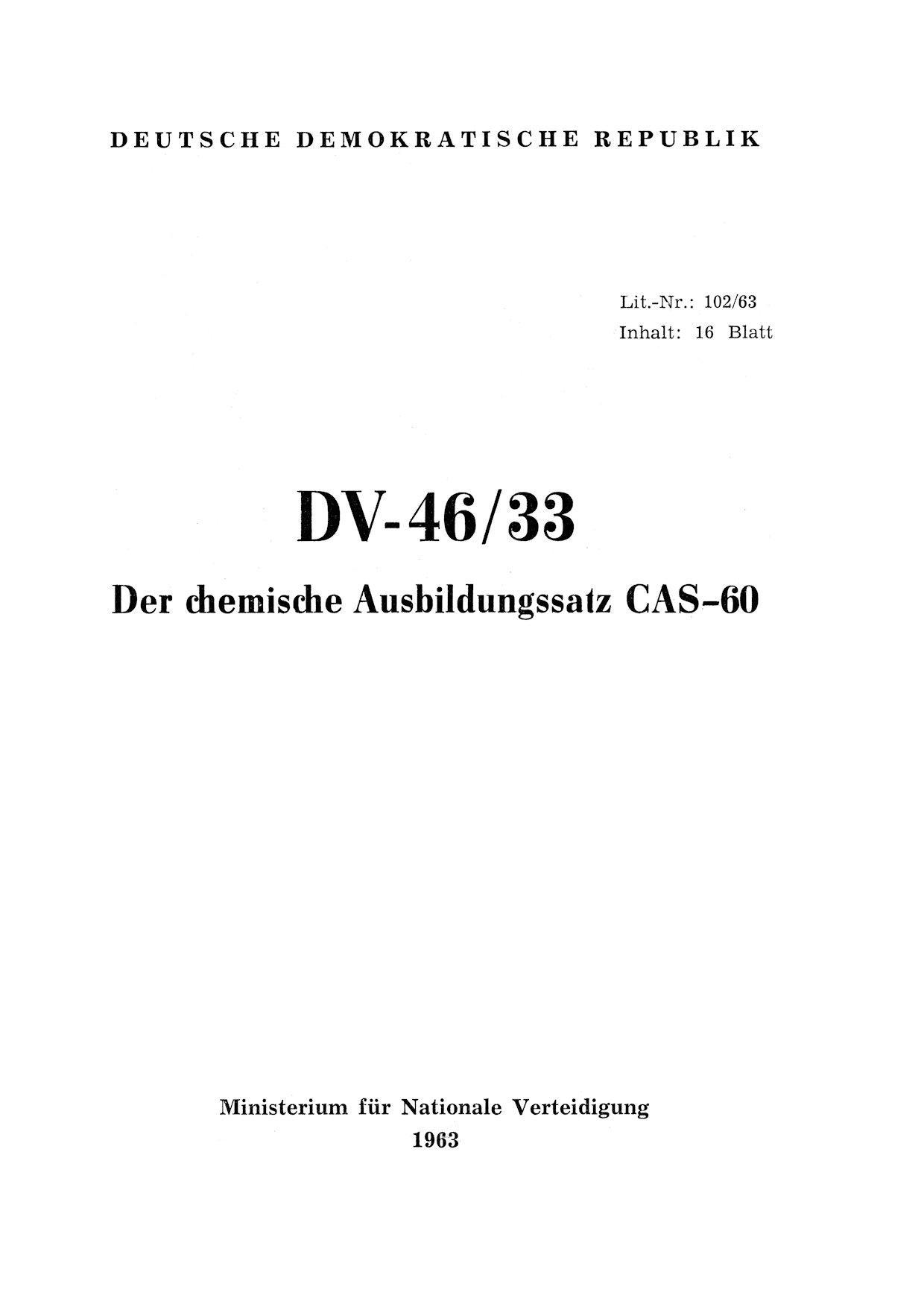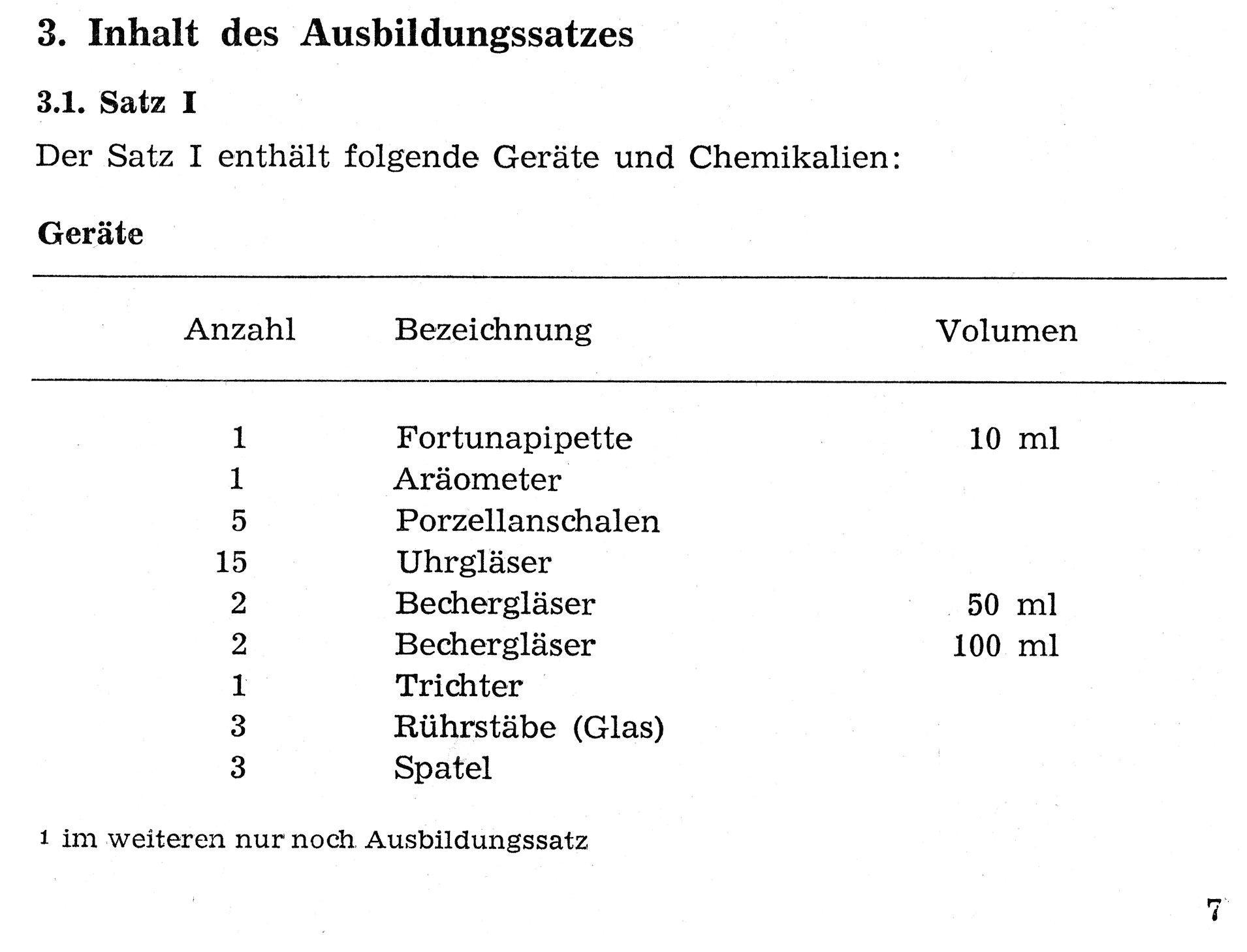
Schriftart NVA-Vorschriften
Hallo, ich habe eine Ergänzung - bzw. auch Frage:
Bei der NVA der DDR wurden Vorschriften und ähnliche Dokumente in der Zeit 1950 bis ca. 1980 mit einem Schriftsatz erstellt, welchen ich bisher nicht zuordnen konnte. Meine Vermutung: der Schriftsatz könnte auch aus der BRD erworben sein... Ungefähr könnte das eine Bodoni sein...
Das könnte die Pergamon sein.
The Pergamon series is a creation of Alfons Schneider (1890–1946) and was issued by the foundry of Ludwig Wagner in Leipzig in 1937/1940, though the website of the Klingspor-Museum says that several of the faces were probably produced after the death of Schneider. This digital version is extended with the necessary OT characters and signs, while also the “символы кириллицы” are added. Also, in addition to the members of the family designed by Schneider, regular, italic, bold and bold italic extended versions were produced. The specimens of Ludwig Wagner stated emphatically: “In allen Graden werden beide K K geliefert”, so these two forms are in all the faces, while the two condensed members also have k k, as the specimens said that this alternative character was also in these two faces.
Hallo, Pergamon kann es nicht sein: z.B. bei Ziffer 1 die Schräge am Kopf, bei der 5 oben rechts das Häckchen... Pergamon wurde von Coen Hofmann erstellt - er wurde 1939 in Amsterdam geboren... Wie ich schon ausführte: die Schrift wurde bereits seit Anfang der 1950-er Jahre genutzt...
Coen Hofmann hat die digitale Version designt. Les dir noch mal den Text zur Entstehung (siehe link) durch oder schau hier:
Eine 5 kann ich in deinem Beispiel nicht finden, da fehlt mir der Vergleich.
Im Anhang eine Textauswahl mit den Ziffern. Dort ist auch die 5 entsprechend zu erkennen.
Hier handelt es sich um die Linotype Excelsior.